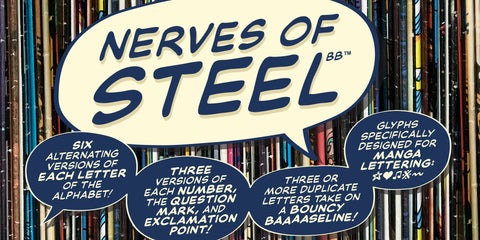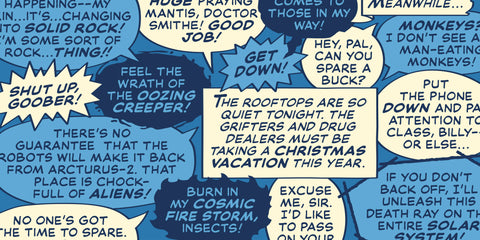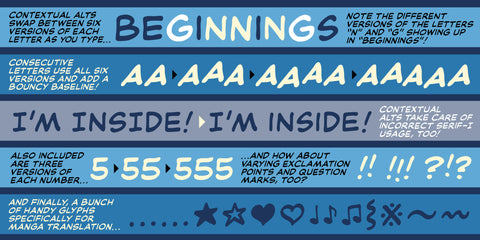
Nerfs d'acier
• Régulier, Italique, Gras, Gras italique
• Comprend des personnages manga et européens
• Les alternatives contextuelles créent six versions alternées de lettres, trois versions alternées de chiffres, de points d'exclamation et de points d'interrogation. Correction automatique des erreurs barrées-I. Trois lettres en double ou plus prennent une ligne de base rebondissante.